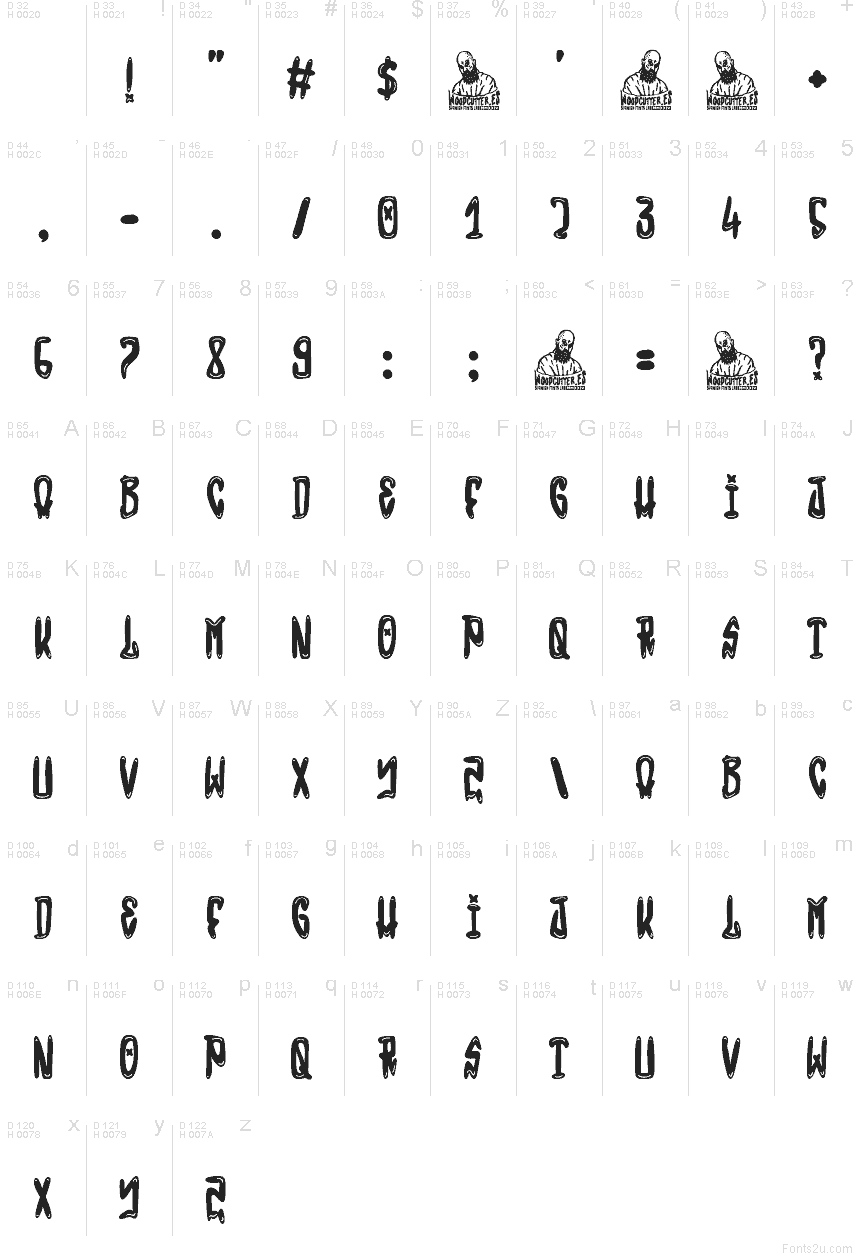
The Bronx Style
The Bronx Style von Woodcutter Manero ist eine kostenlose Graffiti-Schriftart mit hohen, handgezeichneten Buchstaben, abgerundeten Oberkanten und geschwungenen Schnitten, die den Zeichen einen sprühenden Rhythmus verleihen. Die Charaktere kombinieren weiche Bögen mit schärferen inneren Kurven, sodass das gesamte Design wirkt, als wäre es direkt auf eine Wand skizziert worden, anstatt aus starren Vorlagen gesetzt.
The Bronx Style eignet sich hervorragend für Streetwear-Logos, Plakatüberschriften, Albumcover, Event-Flyer, Sticker-Art und urbanes Branding, das eine raue, handgeschriebene Note benötigt. Diese kostenlose Schriftart bringt genug Charakter und Bewegung mit, um kurze Display-Texte zu tragen, während die unebenen Konturen und die markanten Graffiti-Formen sie perfekt für Cover-Art, Skate-Grafiken und andere mutige, dekorative Layouts machen.